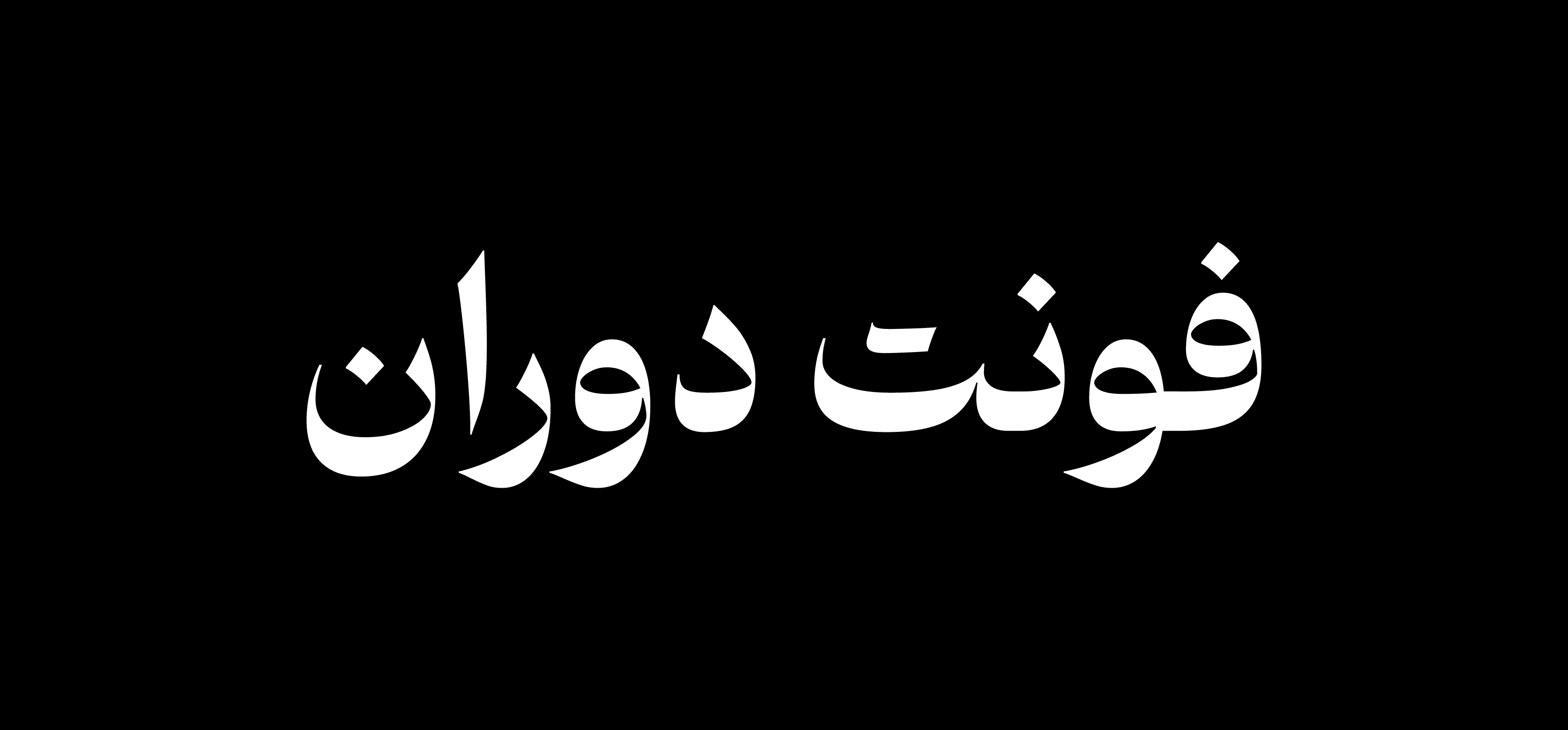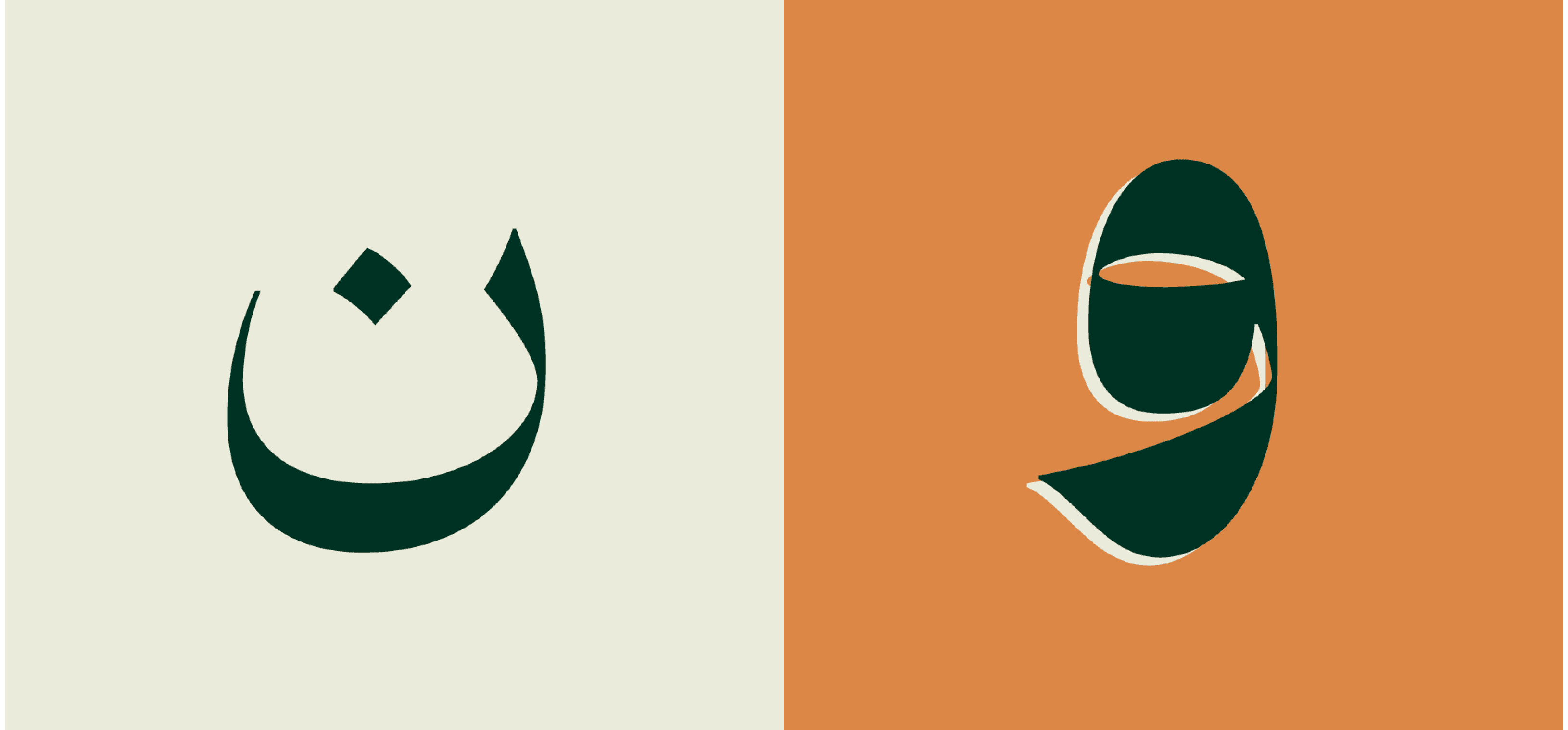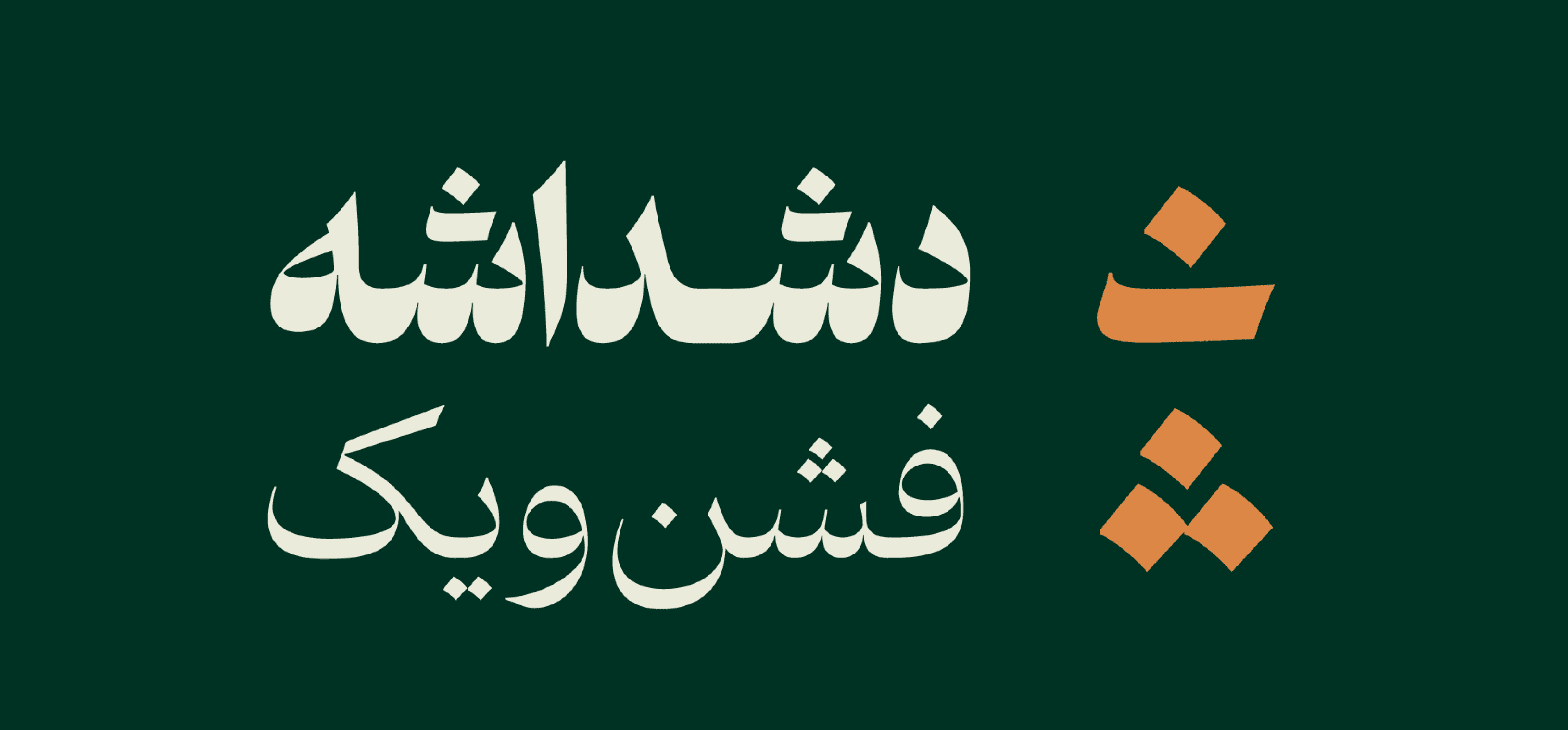
خط دوران بدأ بفكرة مستوحاة من "الفرشة": تصميم خط مختلف يُستخدم في مجال الأزياء. بدأنا العمل بمراجعة الخطوط واختيار خط الثلث كمصدر إلهام، لأنه جذّاب وجريء مثل عالم الأزياء. بدأنا بتصميم وزن ExtraBold. مع الوقت، بدأت لمسات من الثقافة وخط النستعليق بالظهور في التصميم، ربما بشكل غير واعٍ. خط دوران جاد لكنه لطيف. مليء بالمنحنيات، وللعثور على خط مستقيم فيه تحتاج إلى بعض الجهد. المفاصل فيه ناعمة وخالية من الانكسارات غالبًا، بينما الحواف مصممة بشكل حاد. هذه السمات، مع التباين العالي في سماكة الحروف، جعلت الخط أنيقًا وجذّابًا، ومناسبًا بشكل خاص للعناوين.